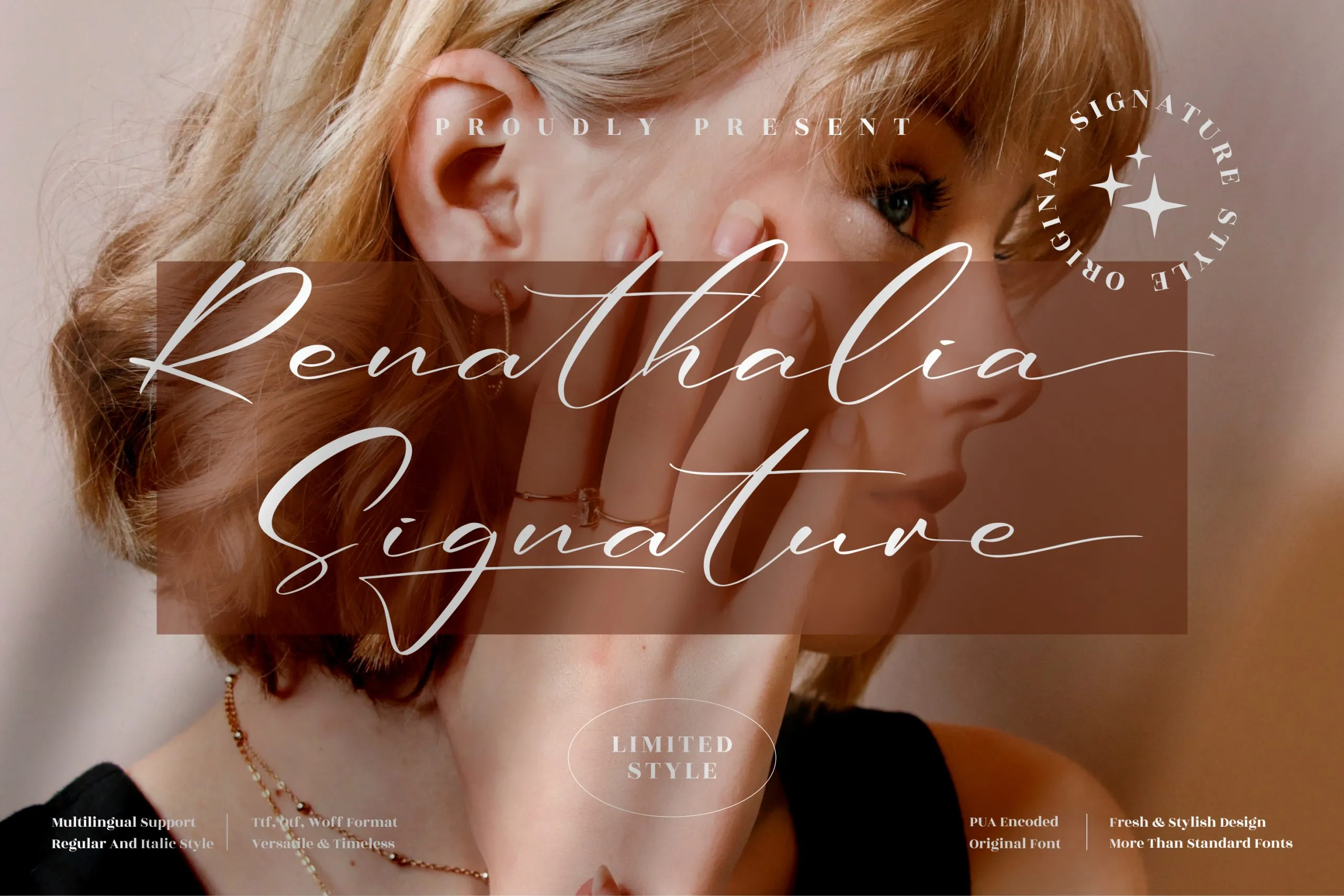
Renathalia Signature Font – Download Grátis
A Renathalia Signature Font é uma elegante fonte que foi criada pelo estúdio Perspectype Studio. Esta premium fonte está perfeitamente adaptada para uma ampla variedade de projetos, desde logotipos e campanhas de marca até ao design de móveis, embalagens de produtos, chás de panela, cartazes, sacolas de compras, carteiras, convites, cartões de cumprimentos, etiquetas, fotografia e até mesmo marcas em eventos especiais. Perfeita para qualquer projeto que deseja um toque de sofisticação, a Renathalia Signature Font é uma escolha ideal para designers gráficos buscando adicionar um toque distintivo aos seus trabalhos. Seja você um designer ou editor de fotos, esta fonte é perfeitamente ajustada ao seu estilo e às suas necessidades específicas.